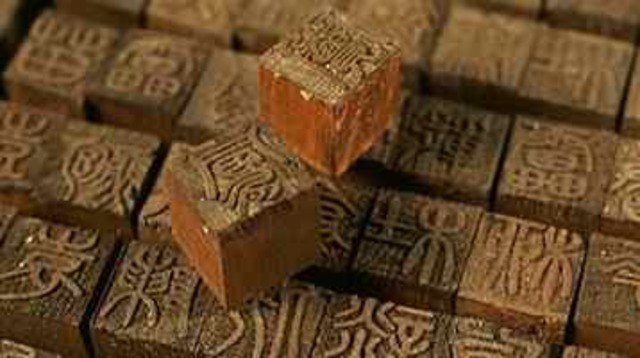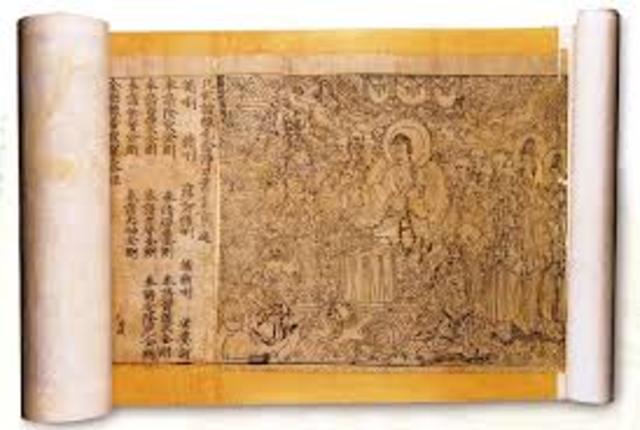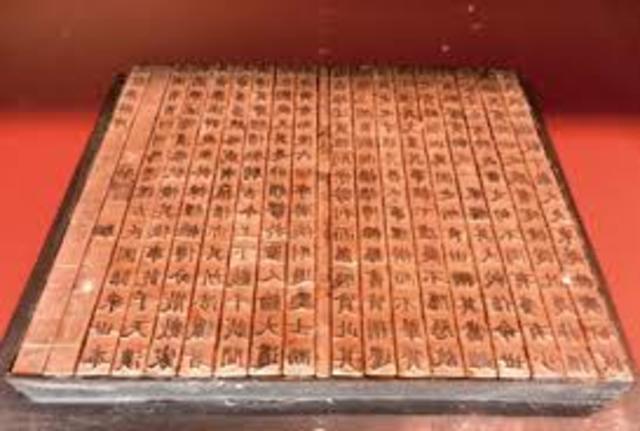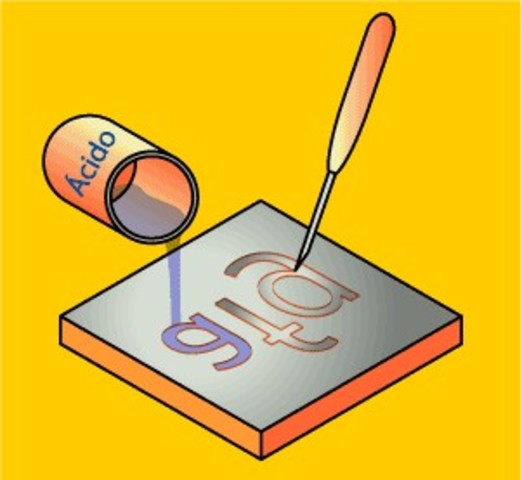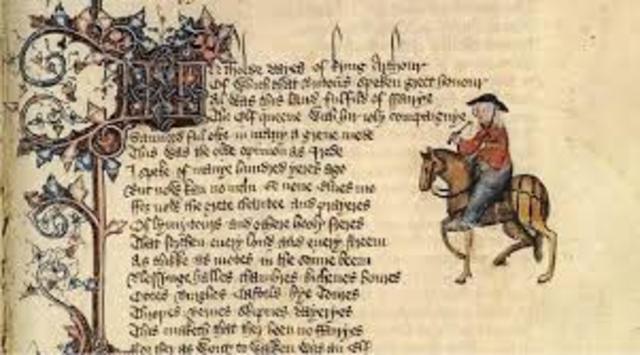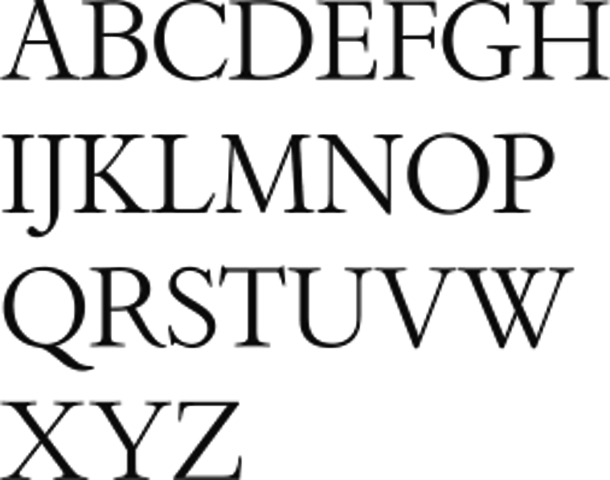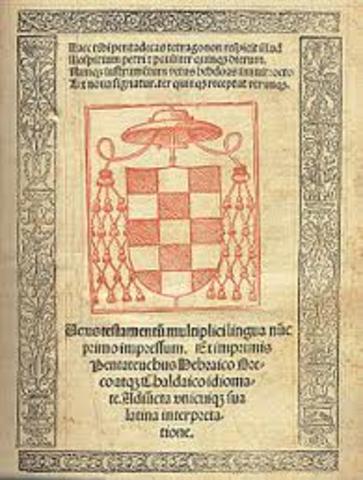
En China se le considera tradicionalmente como el inventor del papel, ya que bajo su administración se perfeccionó la técnica de fabricación del material utilizado para la escritura de documentos, que pasó a tener unas propiedades similares a las del papel actual.
Los caracteres e ideogramas chinos se tallaban delicadamente del revés sobre un bloque de madera y luego se entintaban.
Una copia del Sutra del Diamante, fue encontrado entre los manuscritos de Dunhuang en el siglo XX por Aurel Stein en China, es el libro impreso más antiguo que se conoce
1088 Tipos móviles de Arcilla
El primer sistema conocido de tipos móviles fue inventado en China alrededor de 1088 d. C por Bi Sheng (990-1051). Los tipos creados por Bi Sheng estaban hechos de cerámica. -
La impresión con tipos móviles de bronce fue inventada en China ya en siglo XI en las plancha para la impresión a gran escala para hacer papel moneda, incrustando tipos de metal en la plancha matriz para la lucha contra la falsificación. Hua Sui en 1490 dC, durante la dinastía Ming utiliza este método en la impresión de libros (1368-1644 dC).
La Biblia de Gutenberg, también conocida como la Biblia de 42 líneas o Biblia de Mazarino, es una edición de la Vulgata, impresa por Johannes Gutenberg en Maguncia, Alemania, en el siglo XV. Tras la impresión por el propio Gutenberg del Misal de Constanza a modo de ensayo en 1449, la Biblia es considerada el primer libro impreso a gran escala mediante el sistema de tipos móviles, fue su mayor trabajo y tiene el estatus de icono por simbolizar el comienzo de la «Edad de la Imprenta».
Obres e trobes en lahors de la Verge María es un libro de vital importancia por ser la primera obra literaria impresa en España, escrita en idioma valenciano.
Se fija la primera ortografia de la lengua inglesa.
En 1585 solicitó y obtuvo un decreto de la Star Chamber que le concedió el privilegio para imprimir libros por derecho propio. El rey Carlos I aumentó la independencia y las fronteras de la University Press cuando autorizó a la Universidad para imprimir "todo tipo de libros" concediendo a la Universidad una Carta Magna en 1636.
Franklin no solo imprimió el periódico, sino que también contribuyó con textos bajo seudónimos. Su periódico pronto se convirtió en el más exitoso de las Trece Colonias.